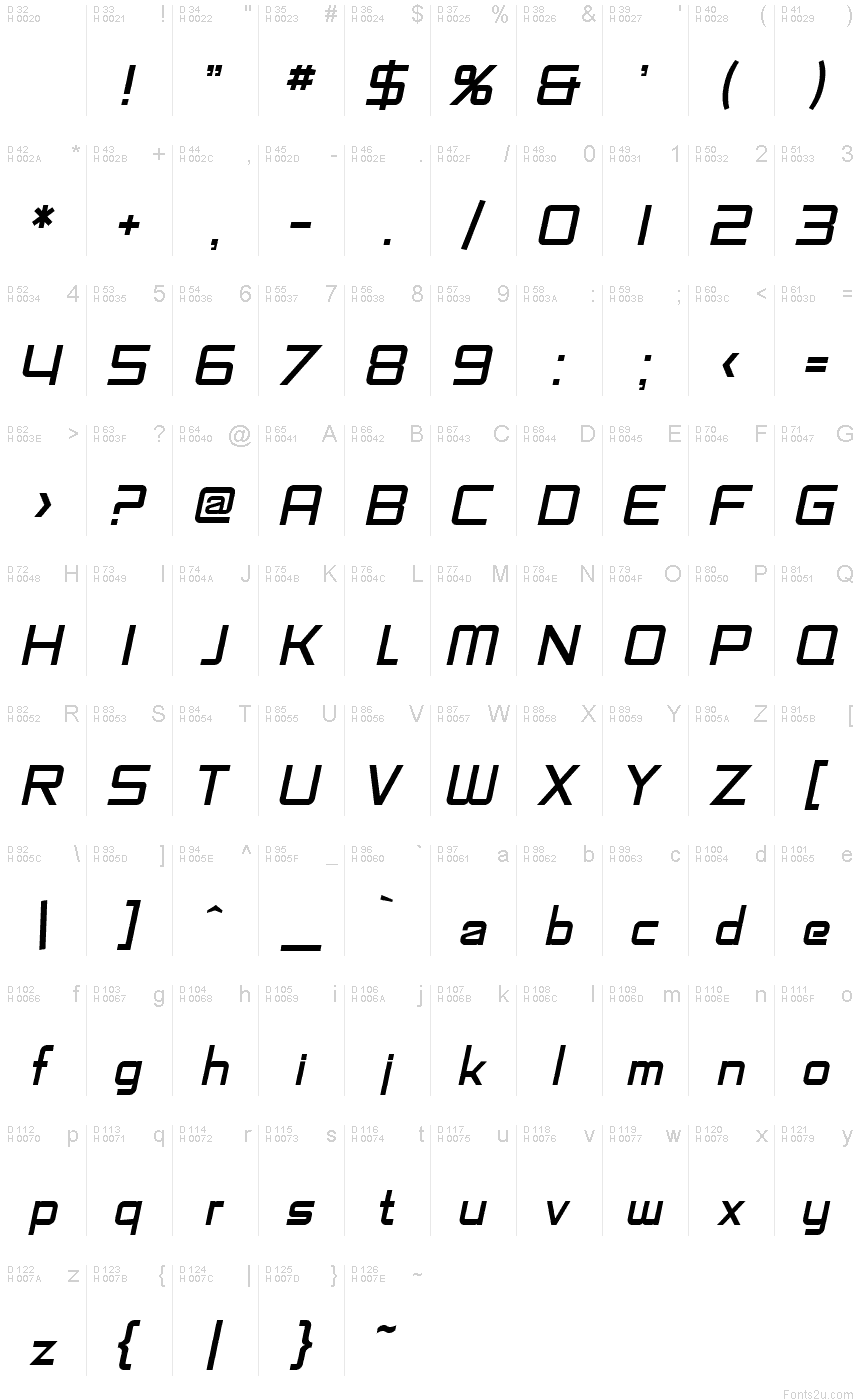
SF Chaerilidae Oblique od ShyFoundry to darmowy, futurystyczny krój typu display o szybkim, pochyłym rytmie oraz szerokich, zaokrąglonych literach. Ścięte narożniki i pozioma dynamika nadają mu elegancki, techniczny sznyt, a zmiękczone krzywizny sprawiają, że nie sprawia wrażenia chłodnego czy mechanicznego.
Ten darmowy font najlepiej sprawdza się tam, gdzie tytuł potrzebuje ruchu i nuty sci-fi: w oprawie graficznej muzyki, brandingu gier, nagłówkach plakatów, na okładkach magazynów czy w napisach tytułowych. Świetnie nadaje się również do krótkich logotypów i znaków graficznych w stylu interfejsów, ponieważ pochyłe i otwarte formy tworzą płynną, skierowaną do przodu sylwetkę, nawet przy użyciu zaledwie kilku liter.
SF Chaerilidae
Oblique
ShyFoundry
Derek Vogelpohl